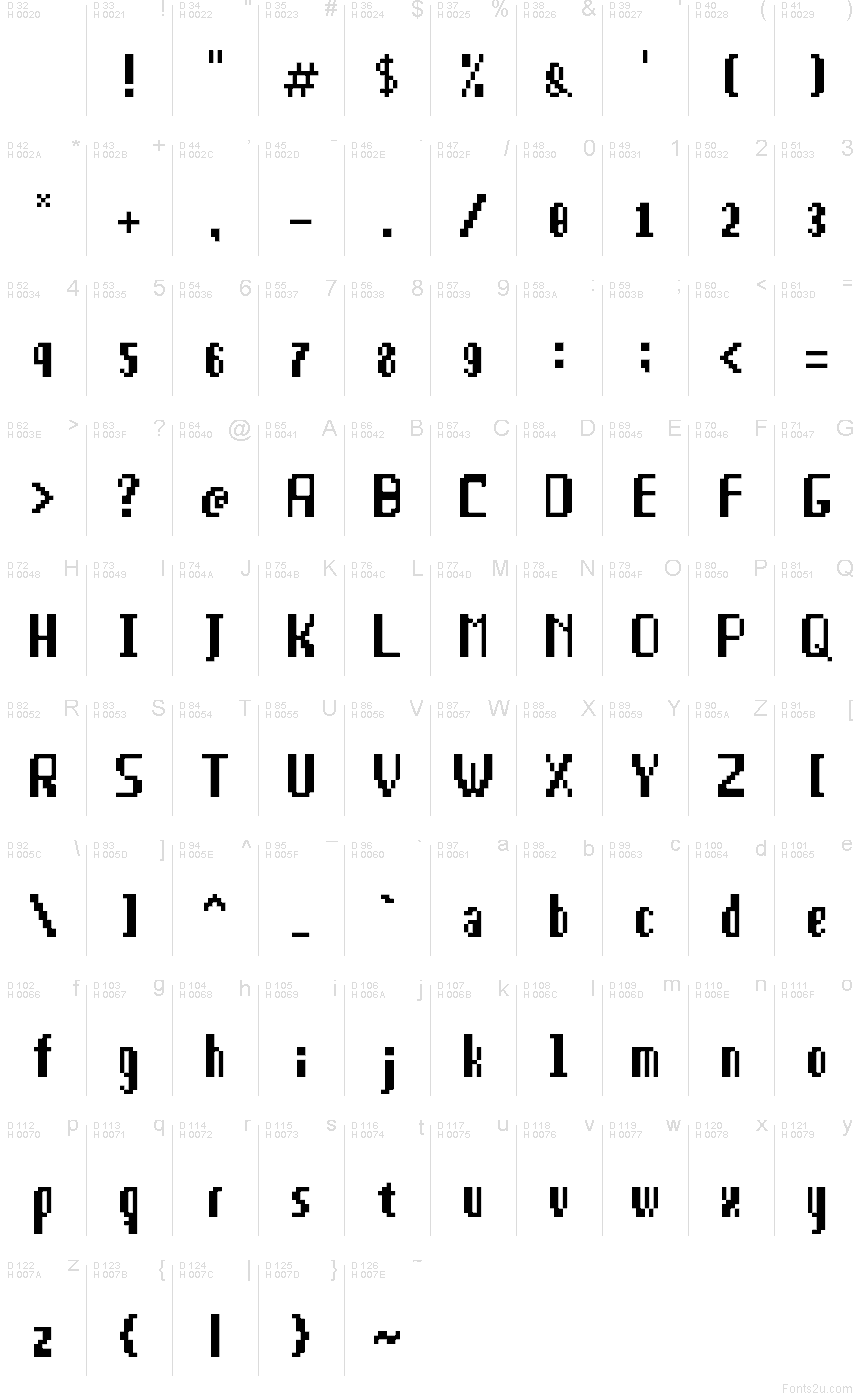
Pup Big é uma fonte bitmap gratuita com um ritmo bruto, que lembra blocos de montar. As letras são construídas a partir de grandes degraus quadrados e recortes profundos, conferindo à fonte uma estética «low-res» saltitante, que fica algures entre os gráficos dos primeiros videojogos e uma etiquetadora robusta.
Adapta-se a cartazes, capas de fanzines, ecrãs de título de jogos, autocolantes, embalagens e cabeçalhos curtos para redes sociais, onde uma fonte gratuita com arestas pixelizadas óbvias deve parecer intencional e não uma nostalgia acidental. Use-a para palavras curtas, emblemas ou composições tipo logótipo, pois o padrão de blocos sobredimensionado confere até às letras simples uma presença robusta e empilhada.